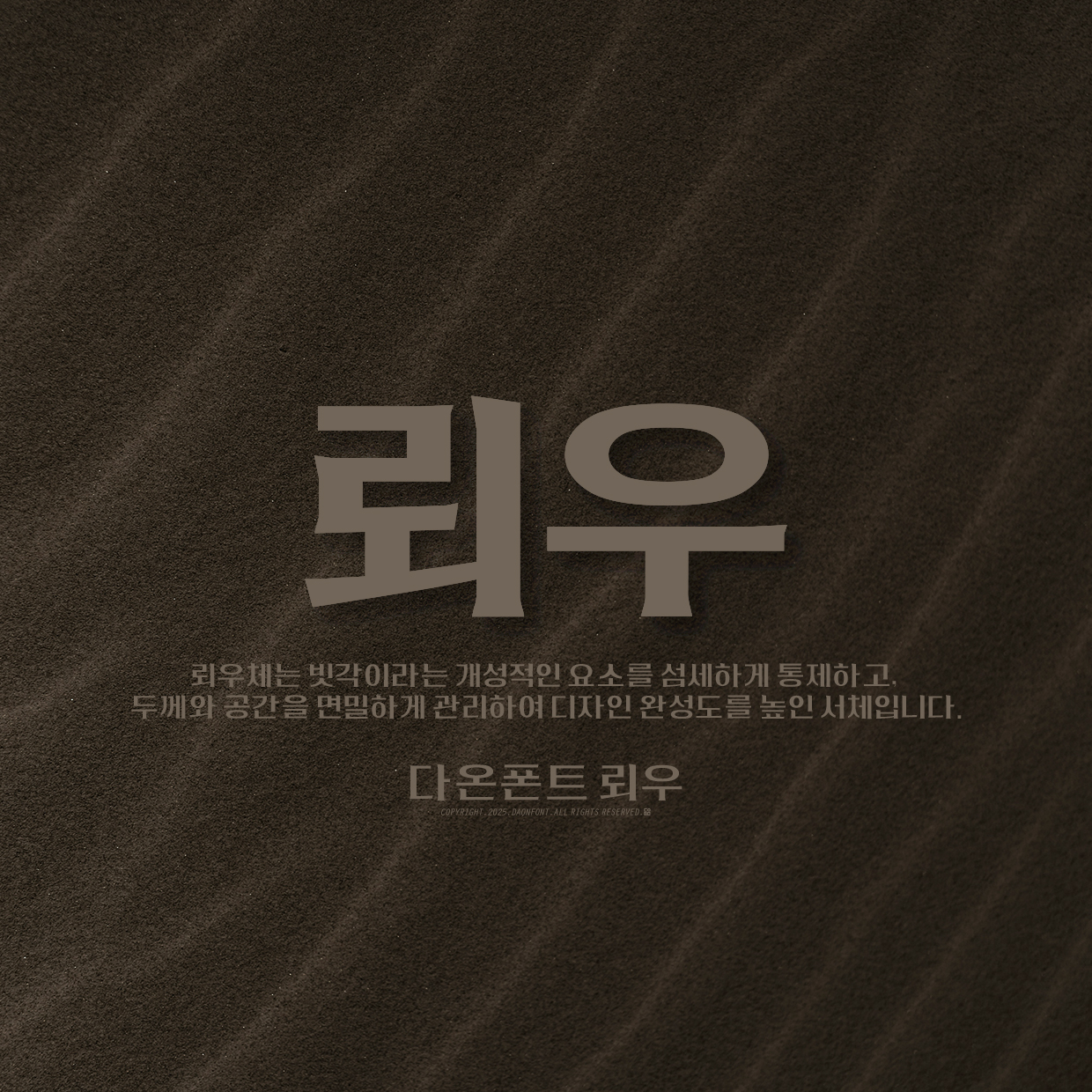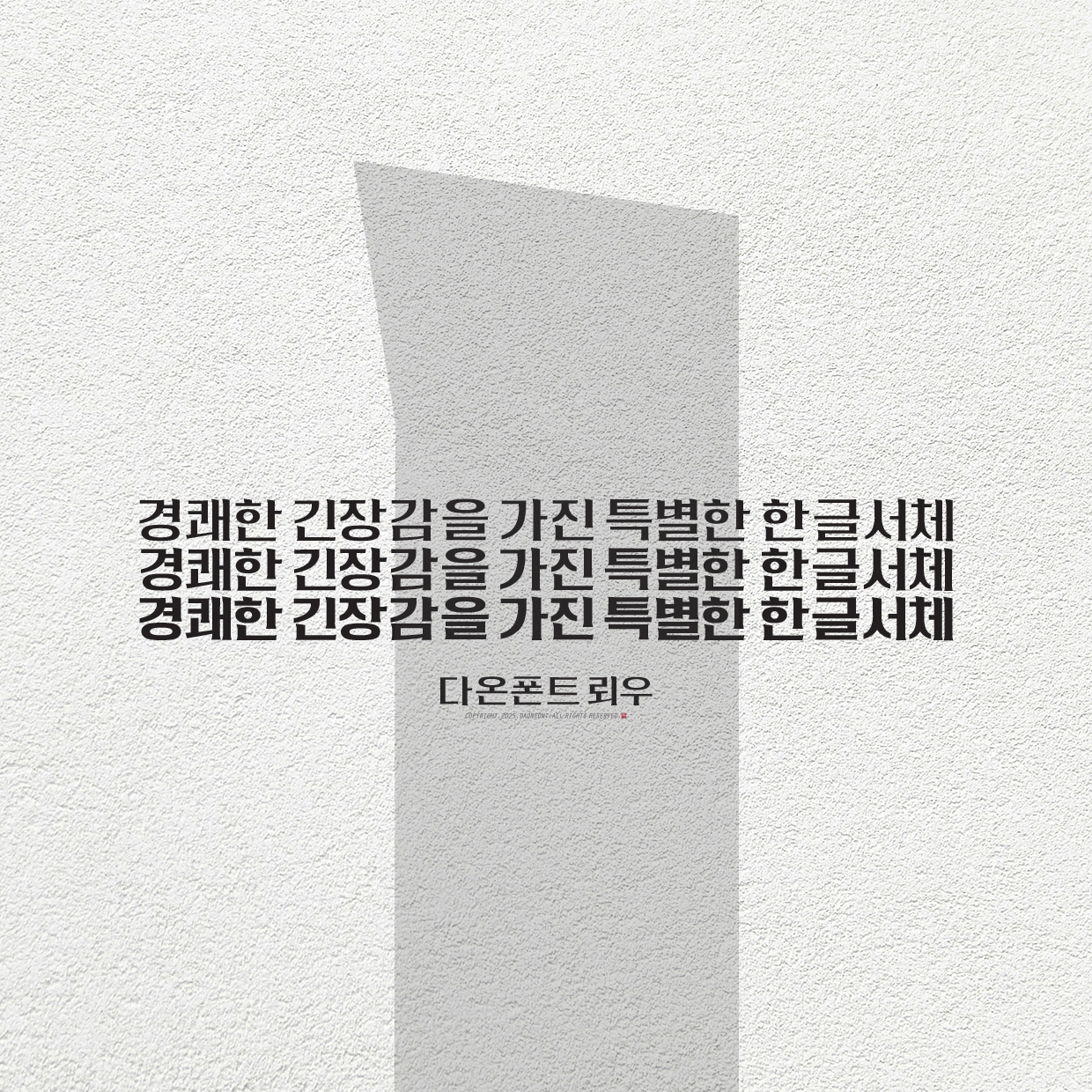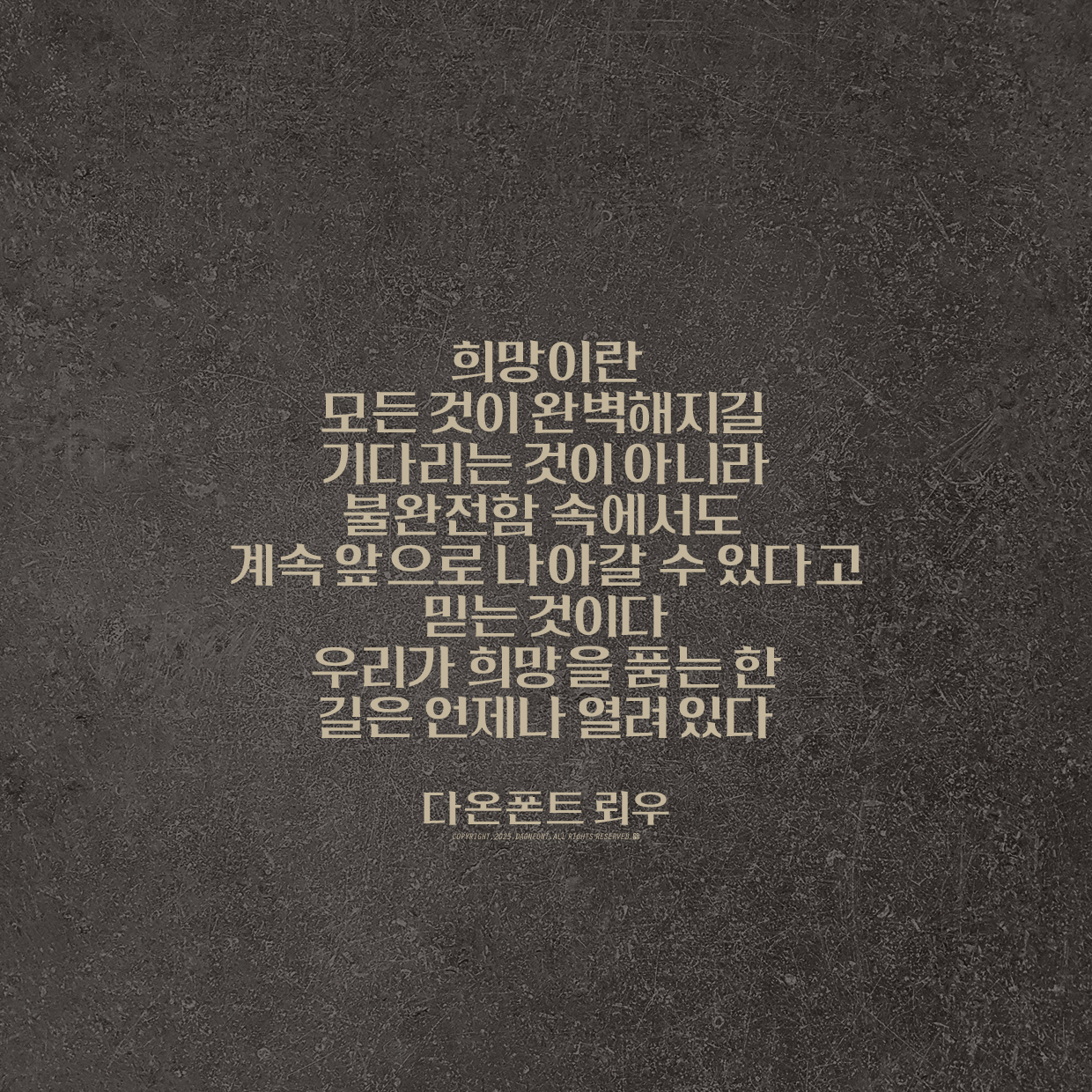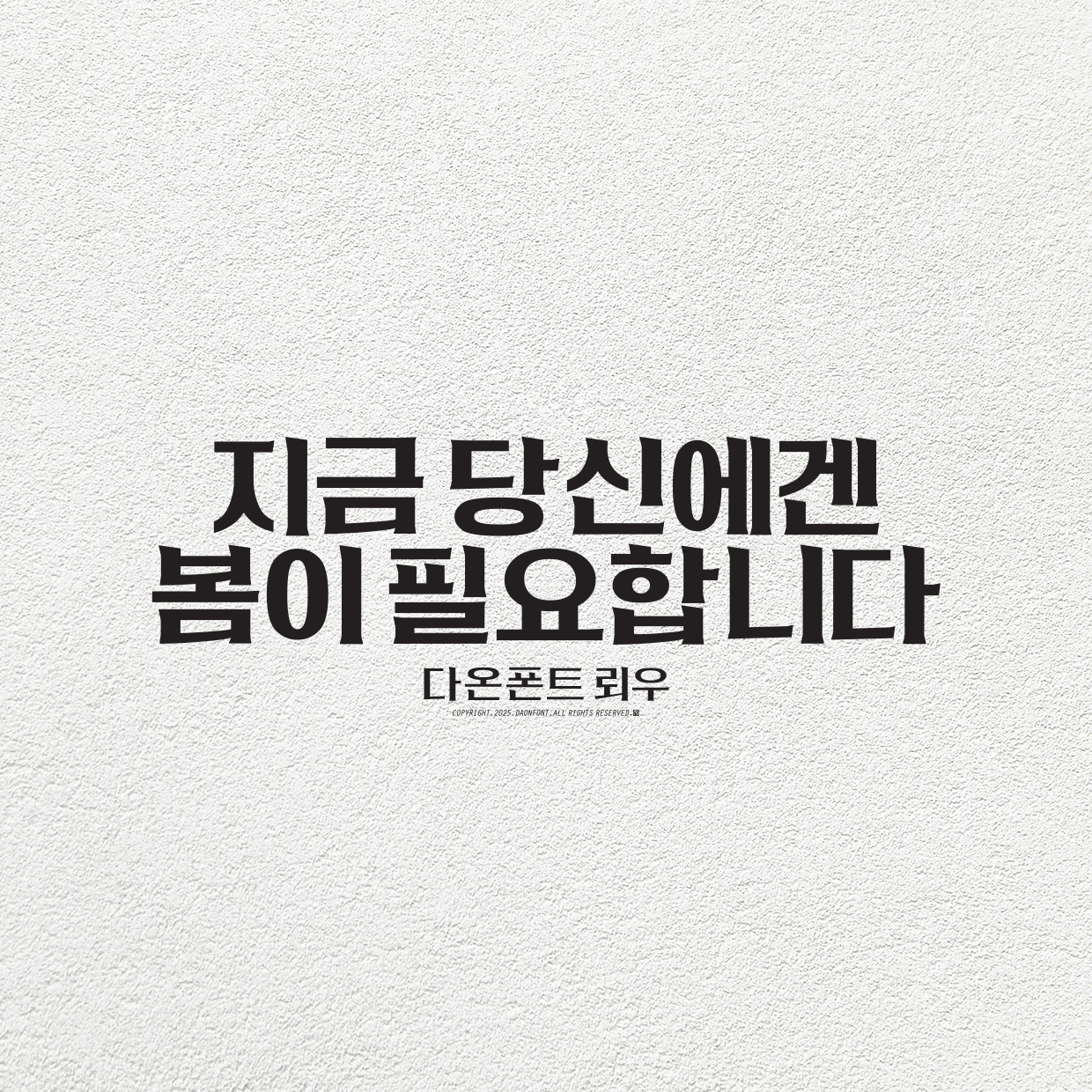
신서체 "뢰우" 3종 제작 안내
다온폰트의 신서체 뢰우 3종의 자소디자인을 마치고 본격적인 교정 작업에 들어갔습니다.
뢰우는 절제된 힘과 현대적 세련미가 균형 있게 어우러진 서체로,
글자 간의 공간과 호흡을 섬세하게 설계하여 가독성과 미감을 높였습니다.
정교한 디테일과 안정적 구조를 바탕으로, 다양한 활용성을 목표로 완성도를 높여가겠습니다.